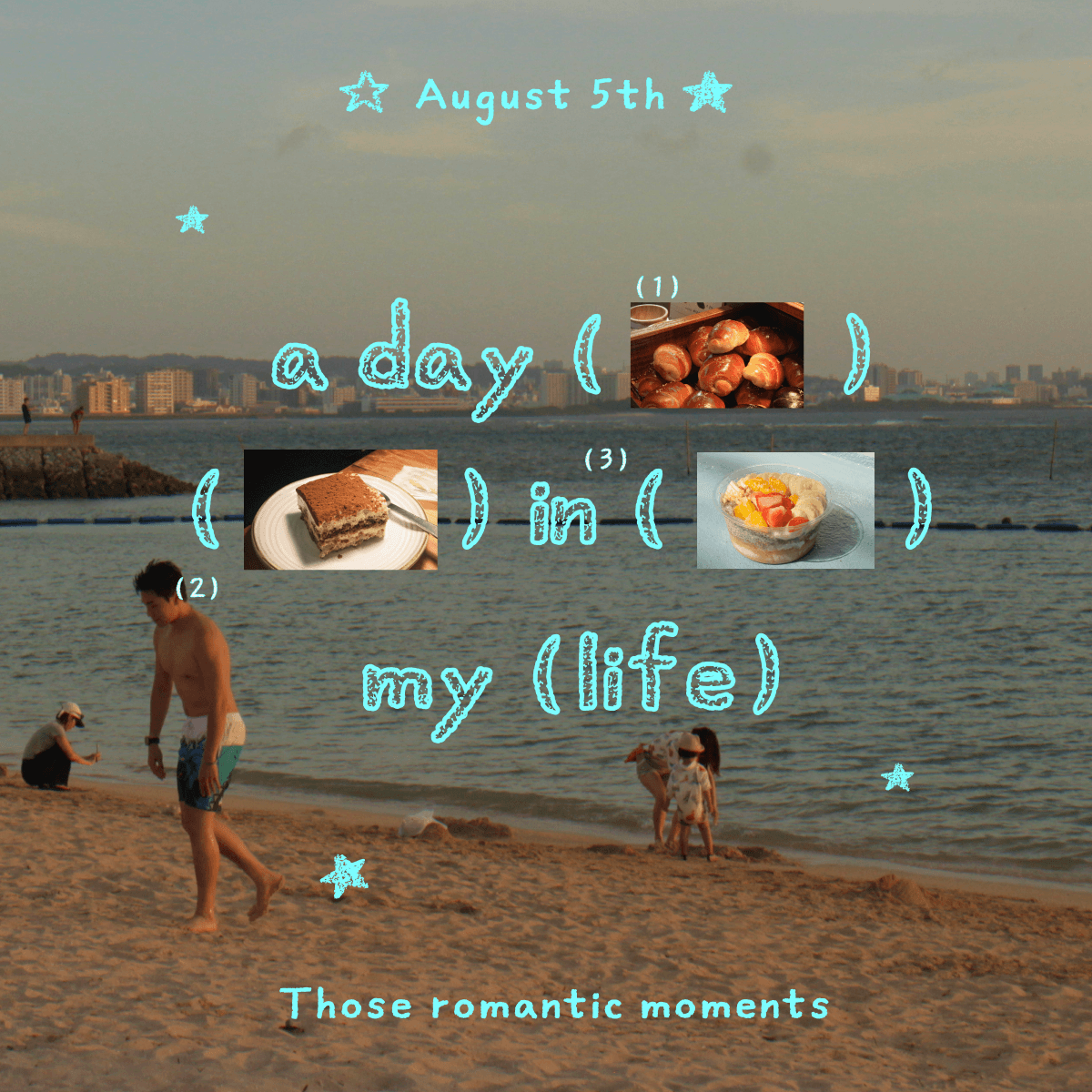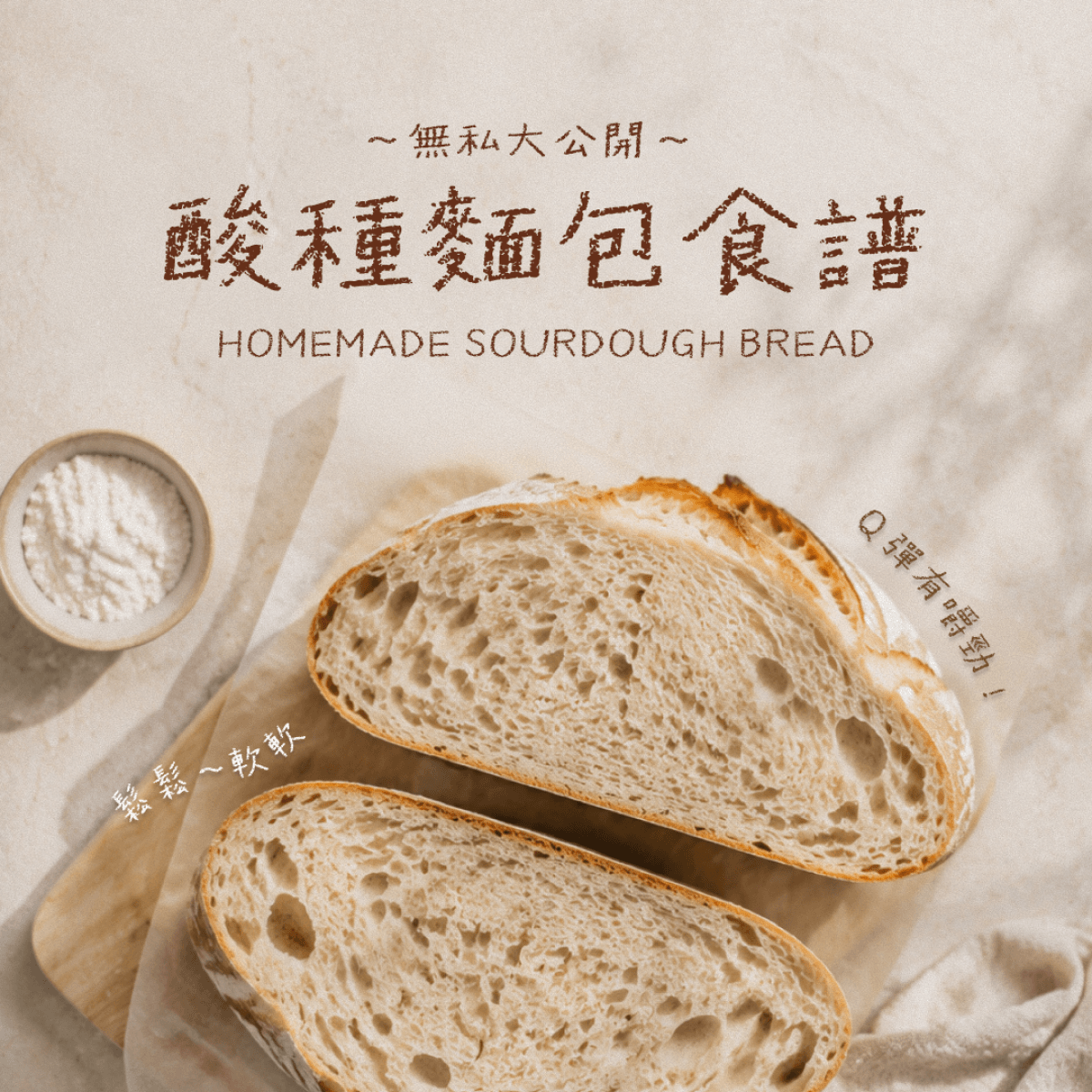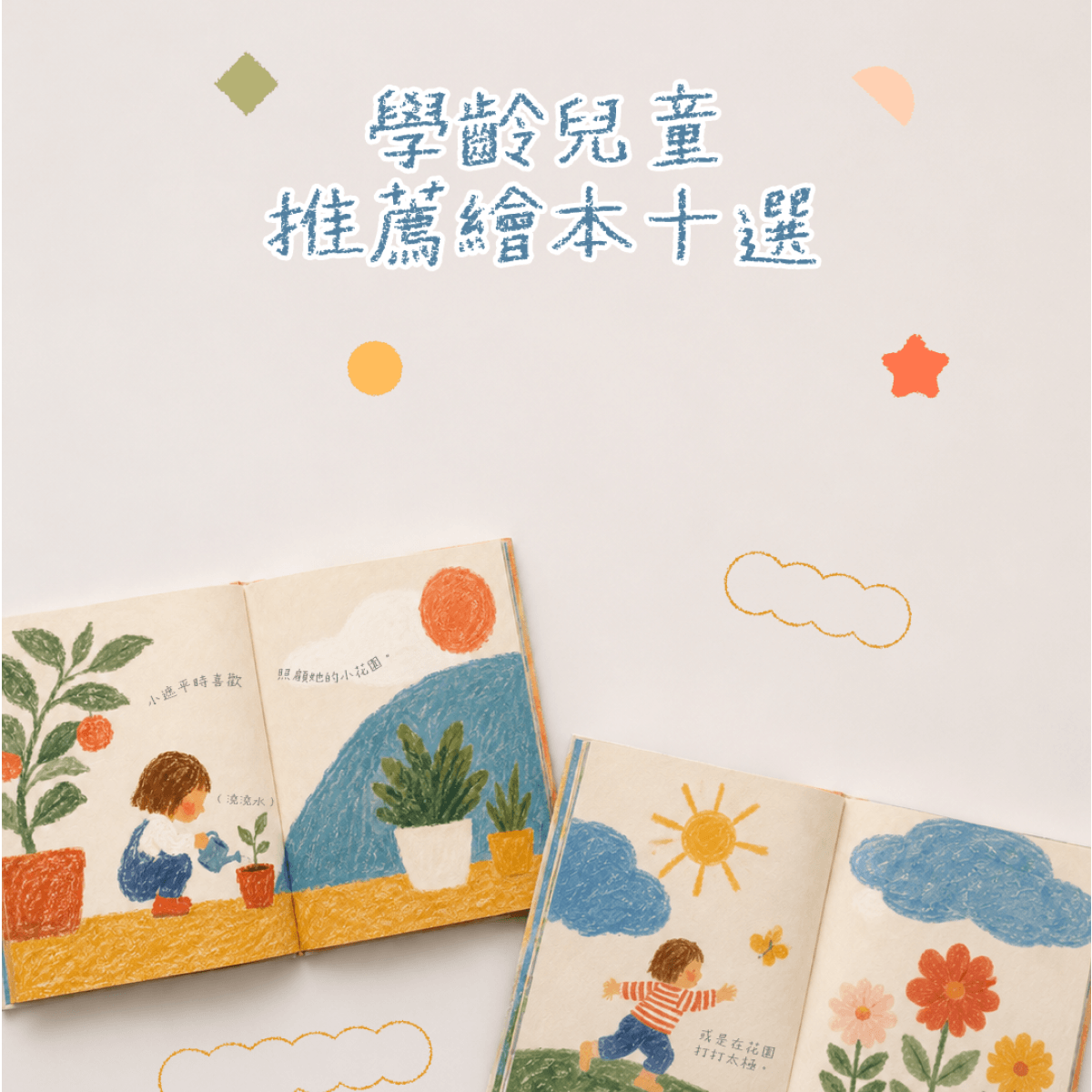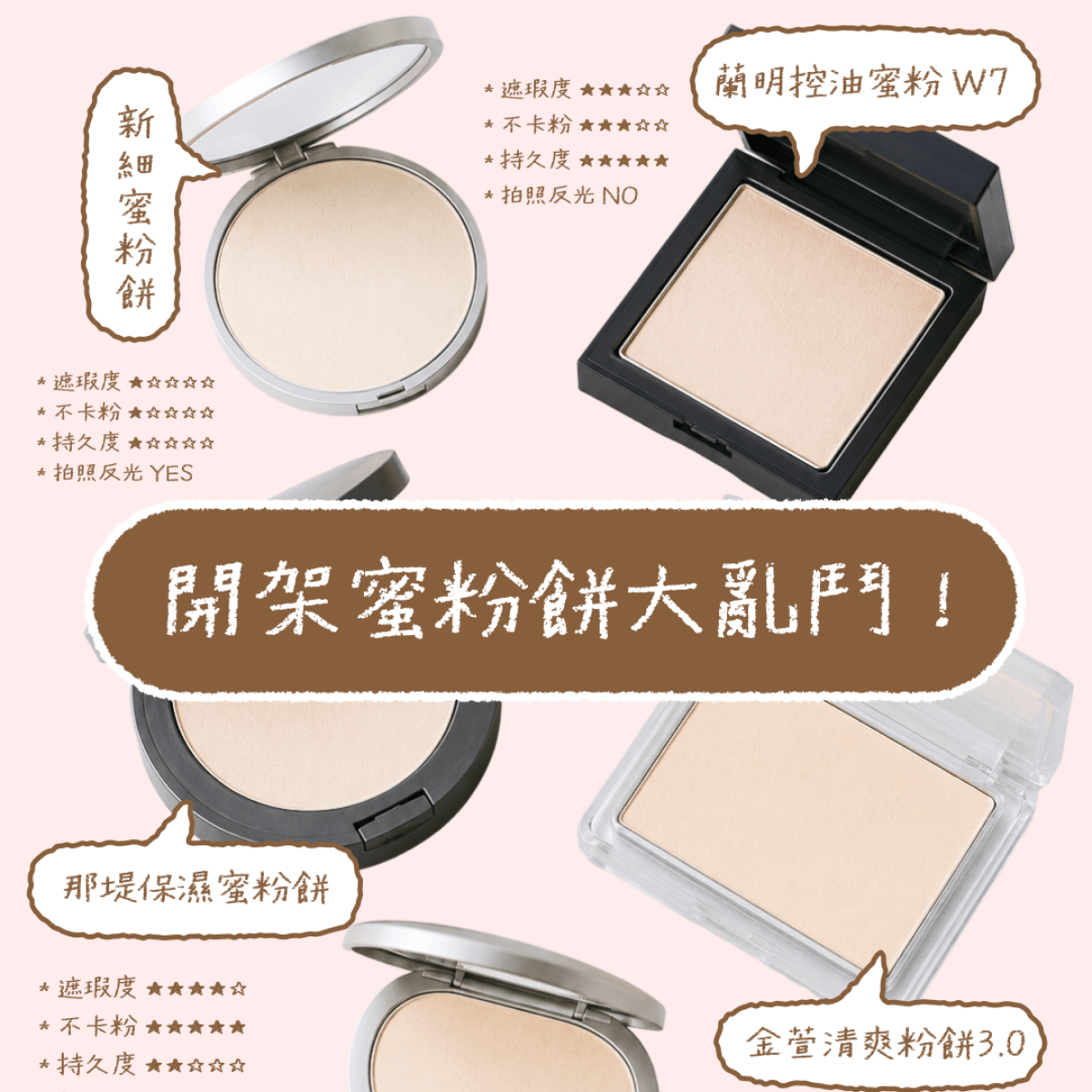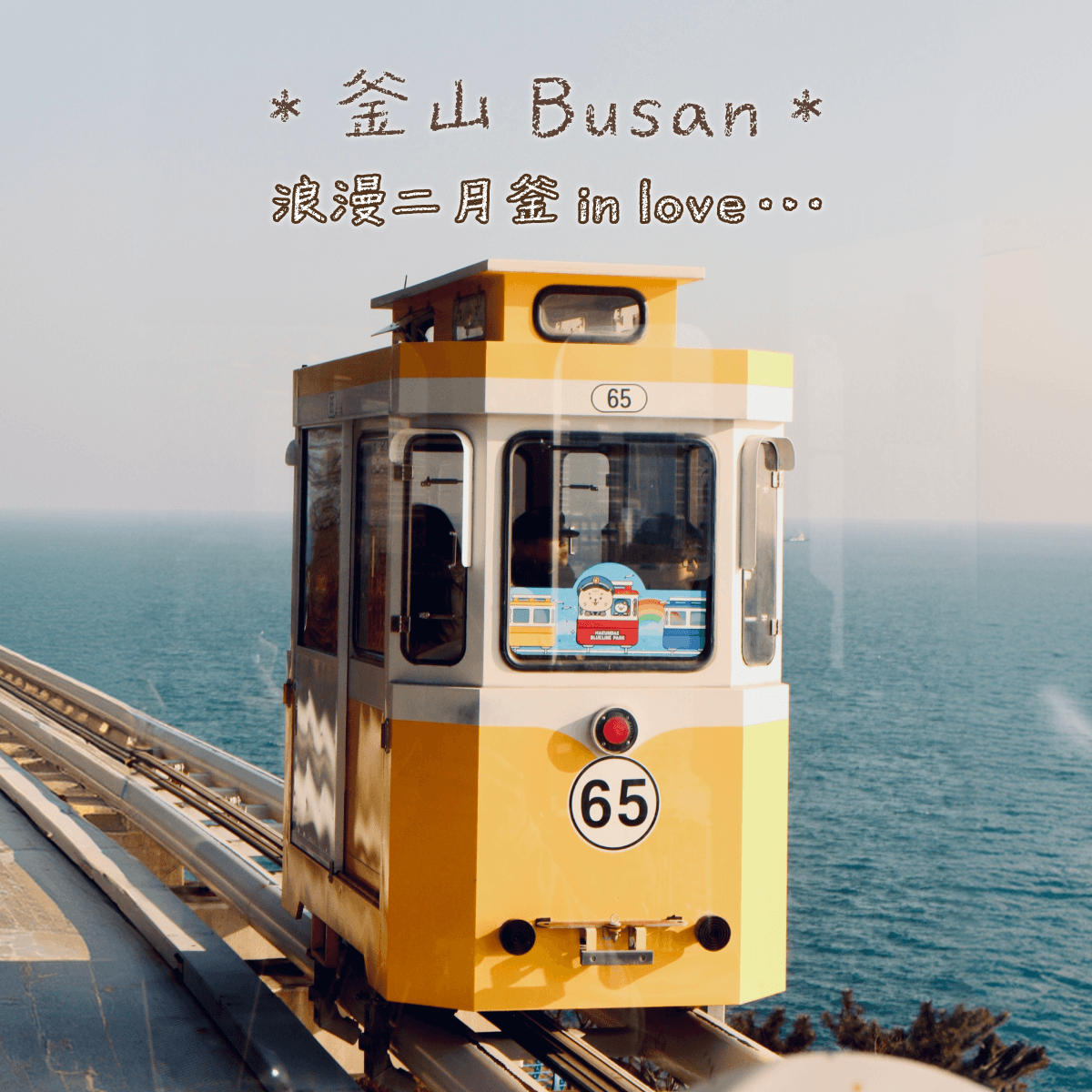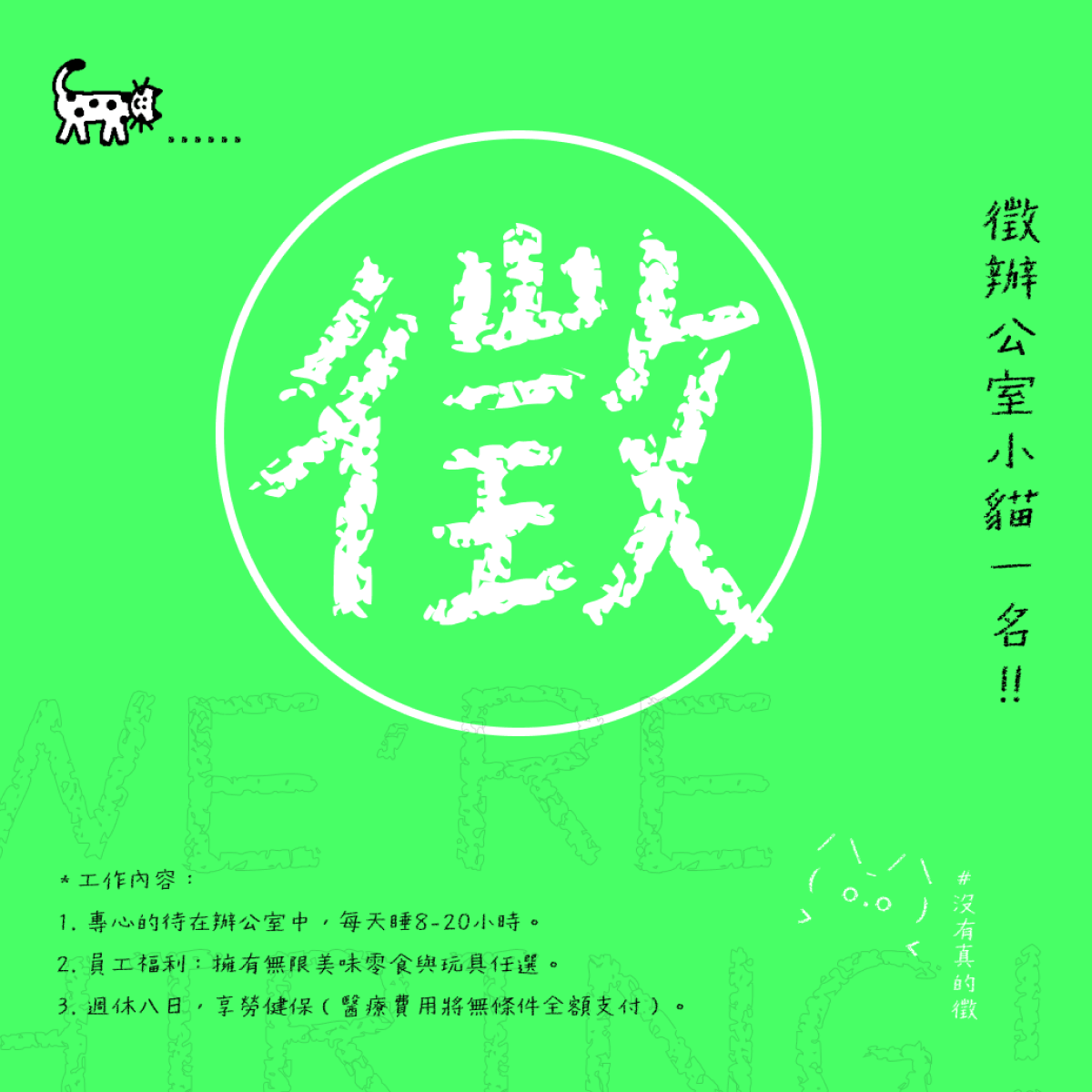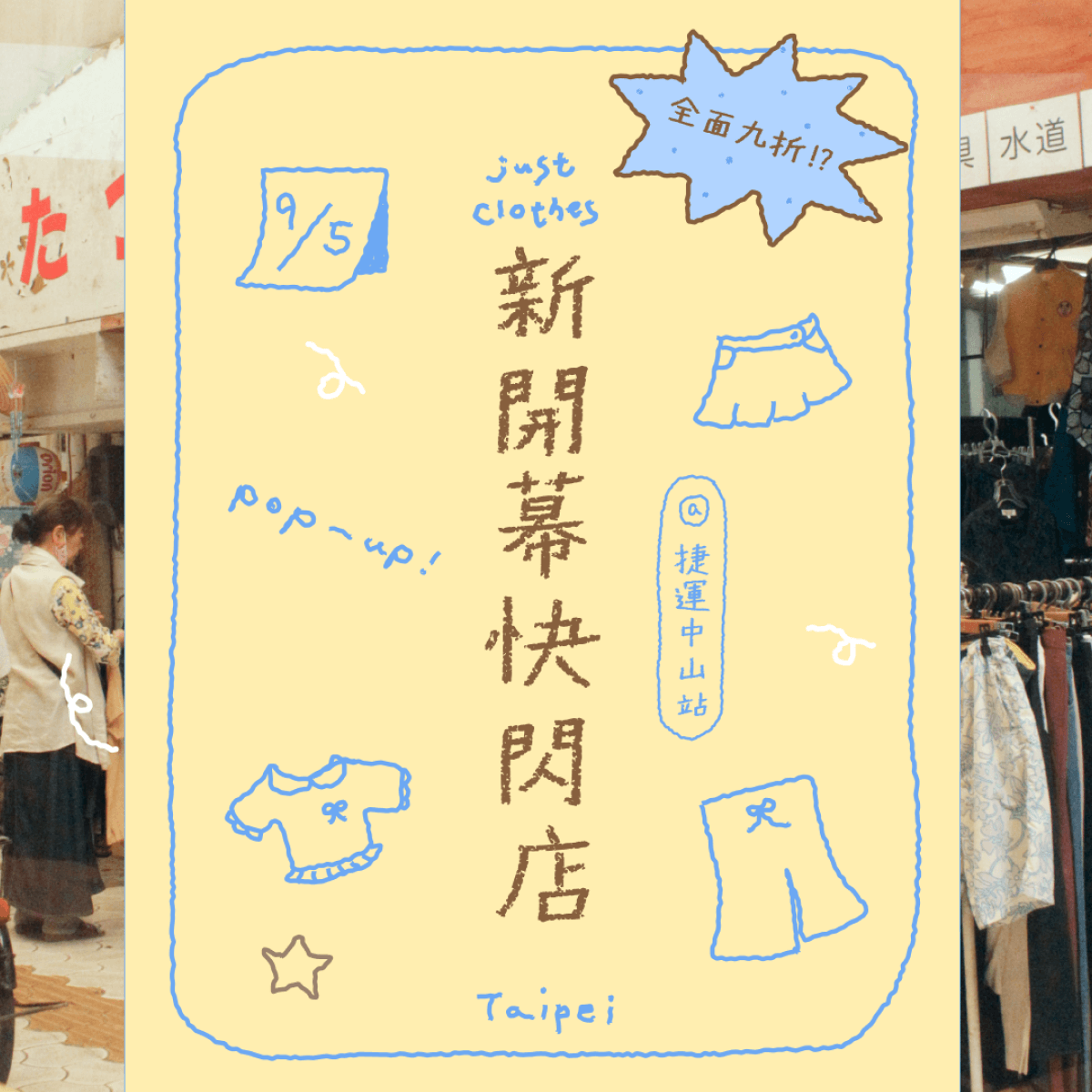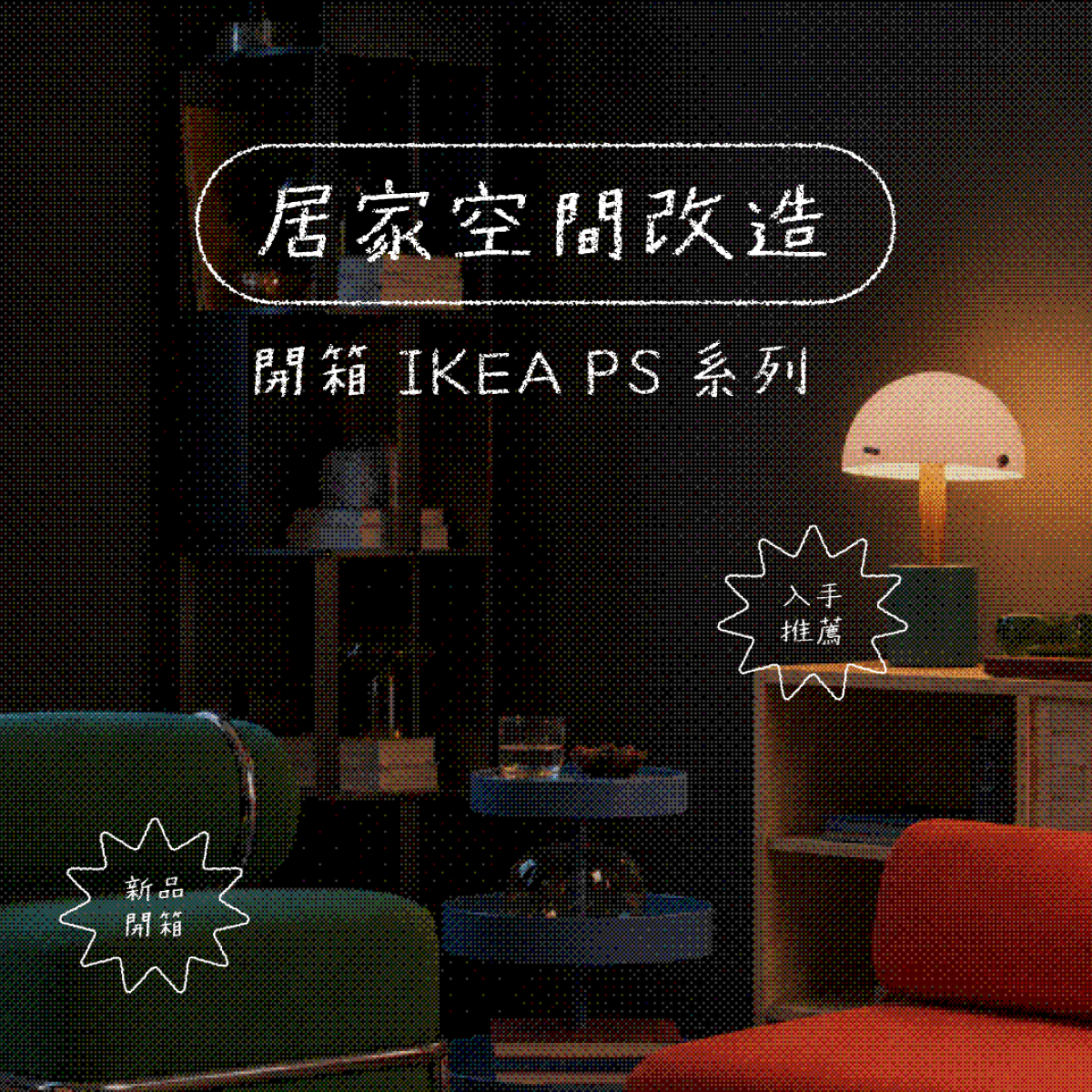
值日生粉筆體
宇宙無敵,青春俏皮!純手工粉筆字,自然有人味。由圖文作家薛惠瑩一筆筆書寫,justfont 設計師精細修整而成。品質可靠、溫暖有特色。
字型設計師
薛慧瑩
插畫工作者。興趣是做陶,喜歡以人、植物、生活、飲食為創作的題材,作品散見於各類書籍報紙雜誌。 著有《1個媽媽2個頭大》、《大的小的——媽媽與小孩的日常生活大戰》。繪有《晚安,10隻小羊》、《貓房子》、《巨人的眼淚》、《注音練習》、《夢遊》、《阿茲海默先生》等繪本。